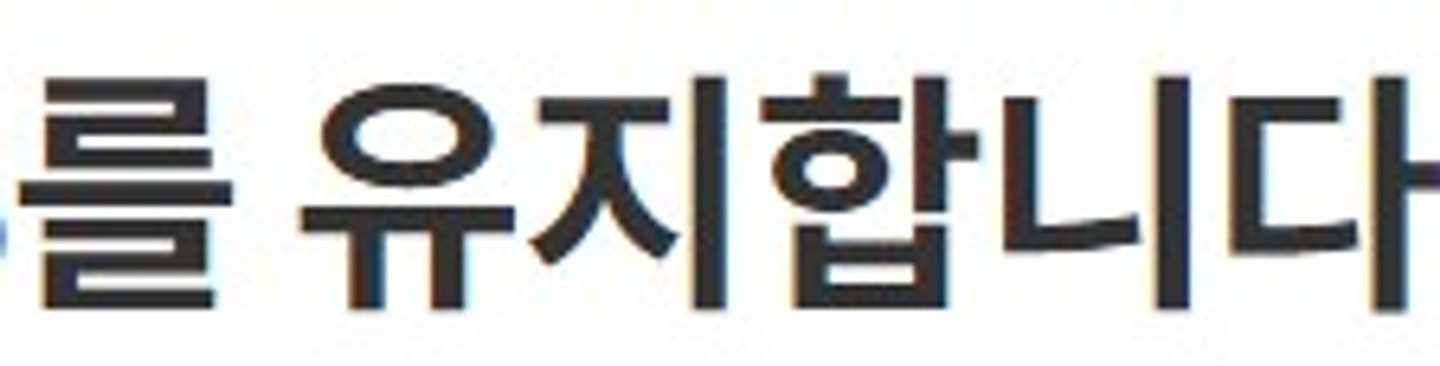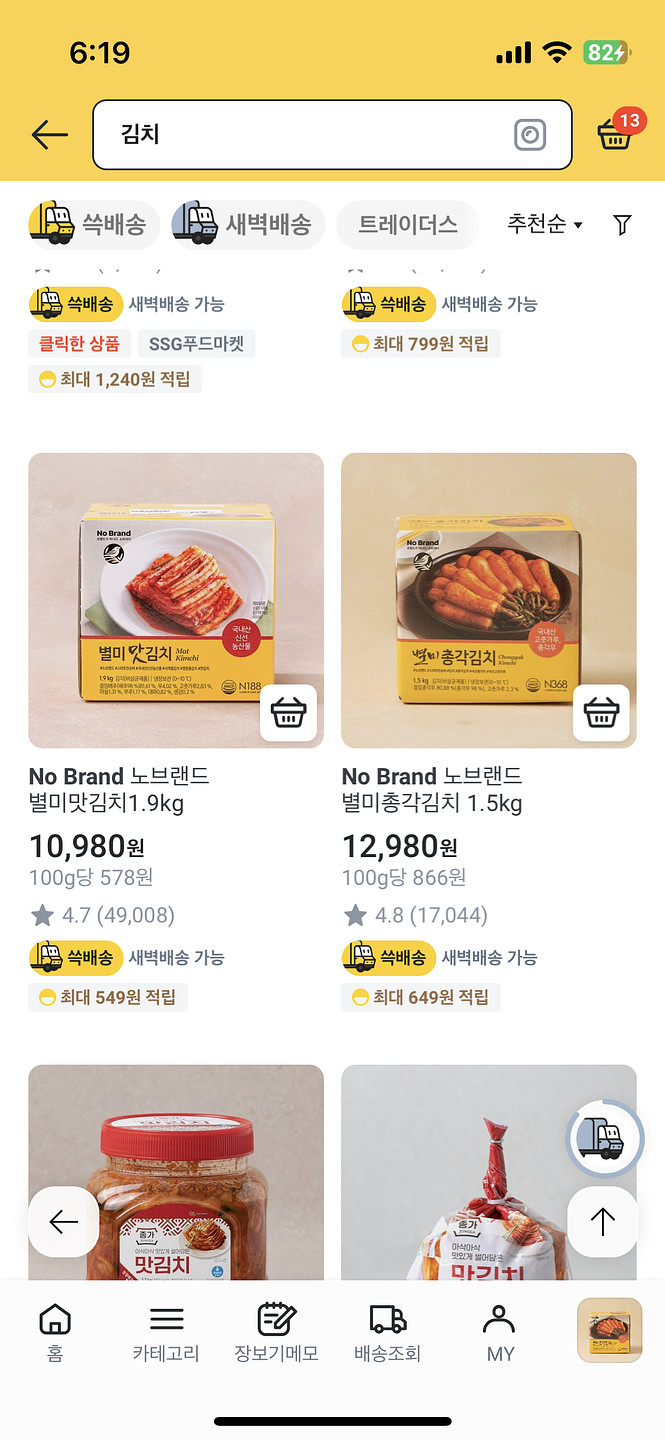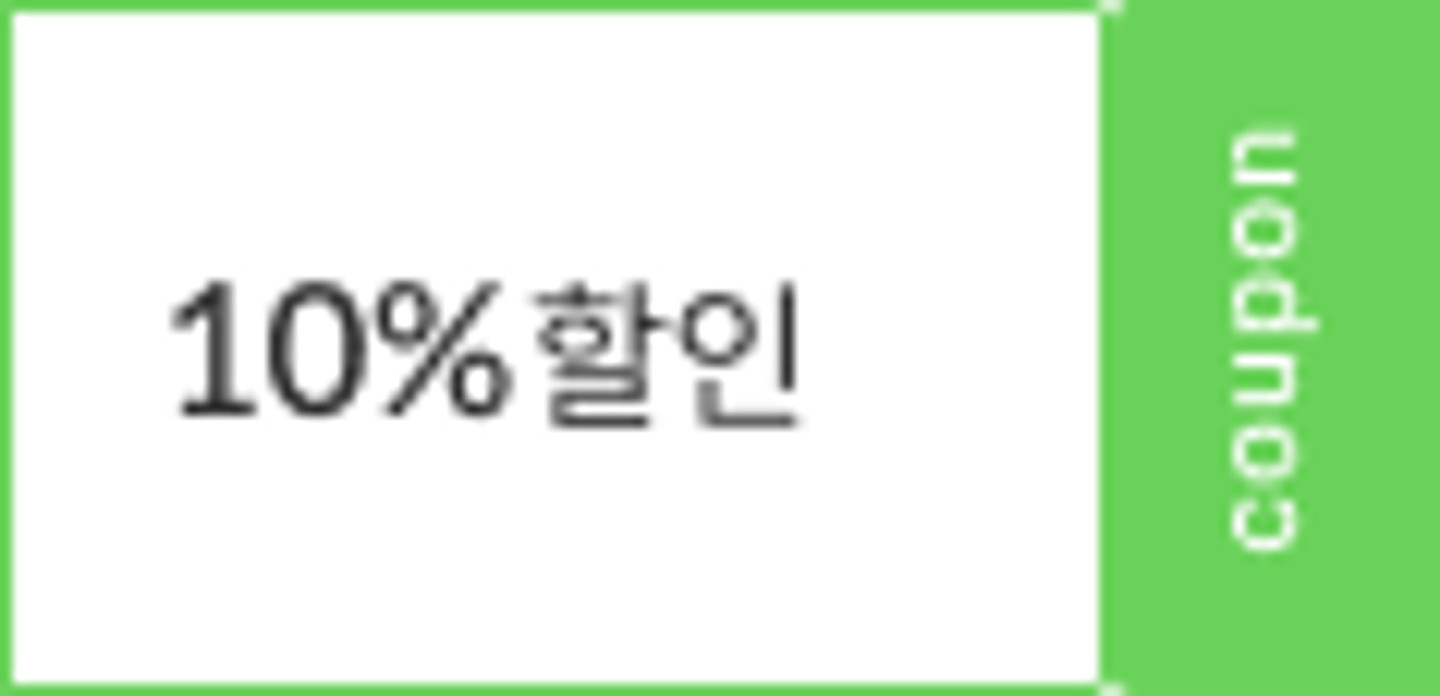
안녕하세요. Clipchamp에서 동영상 편집 중에 썼던 폰트입니다. 다 영어 폰트라 변경을 해봐도 변하질 않아서 도통 무슨 폰트인지 모르겠습니다. 혹시 무슨 폰트인지 알수있을까요?? 감사합니다 (꾸벅)
여기 사용된 폰트 알고 계신 분 있으실까요.. 이미지 찾기를 하면 다 다르게 나와서 모르겠네요ㅠㅠ 프리텐다드, SUIT, 스포카 한 산스 네오, 민산스 다 나오네요.... 감사합니다..
몇천만원주고 홈페이지 개발해놓고 psd 안받아놓은 바보같은 회사때문에 킹받네요.... 10% <-이 폰트는 대체 대조해봐도 찾기가 어렵네요... 본고딕도 노토산스도 아니더라구요.... 대체 저 폰트가 뭘까요?ㅠㅠㅠㅠ 할인<-이 글씨야 노토산스하면되는데... % 형태가 맞는게 없어요... 쿠폰을 대대적으로 다 수정해야되는데...막막합니다..ㅠㅠㅠ 10% 할인<- 이 폰트 뭔지 아시는분!!!!!!!!! 도와주세요!!!!!!!!
윤고딕330, 스포카 한 산스 네오[Spoqa Han Sans Neo] TTF 04 Medium 모두 적용해 보았는데, ' ' 따옴표가 맞지 않아 이에 맞는 글꼴을 찾고 있습니다..!